今回は「題」の書き方を解説します。
「題」の見本
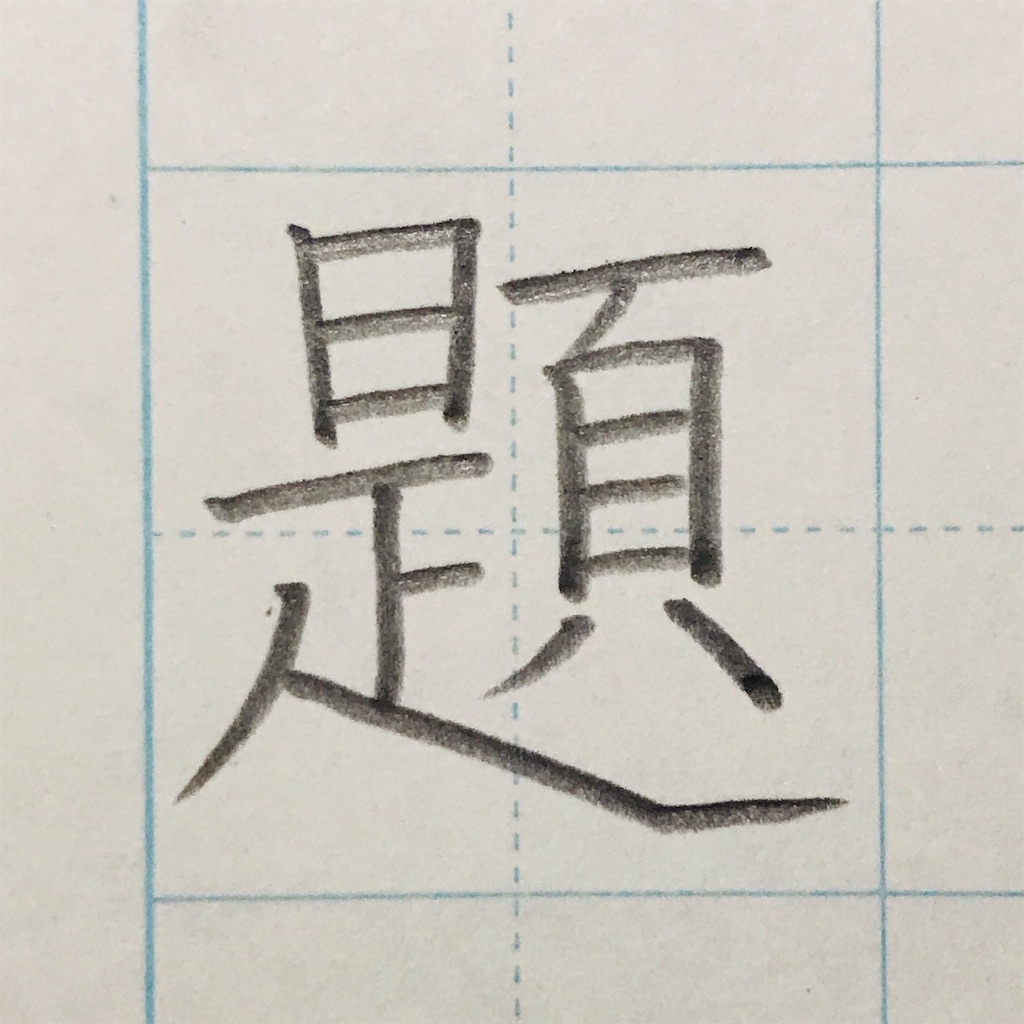
「題」の画数
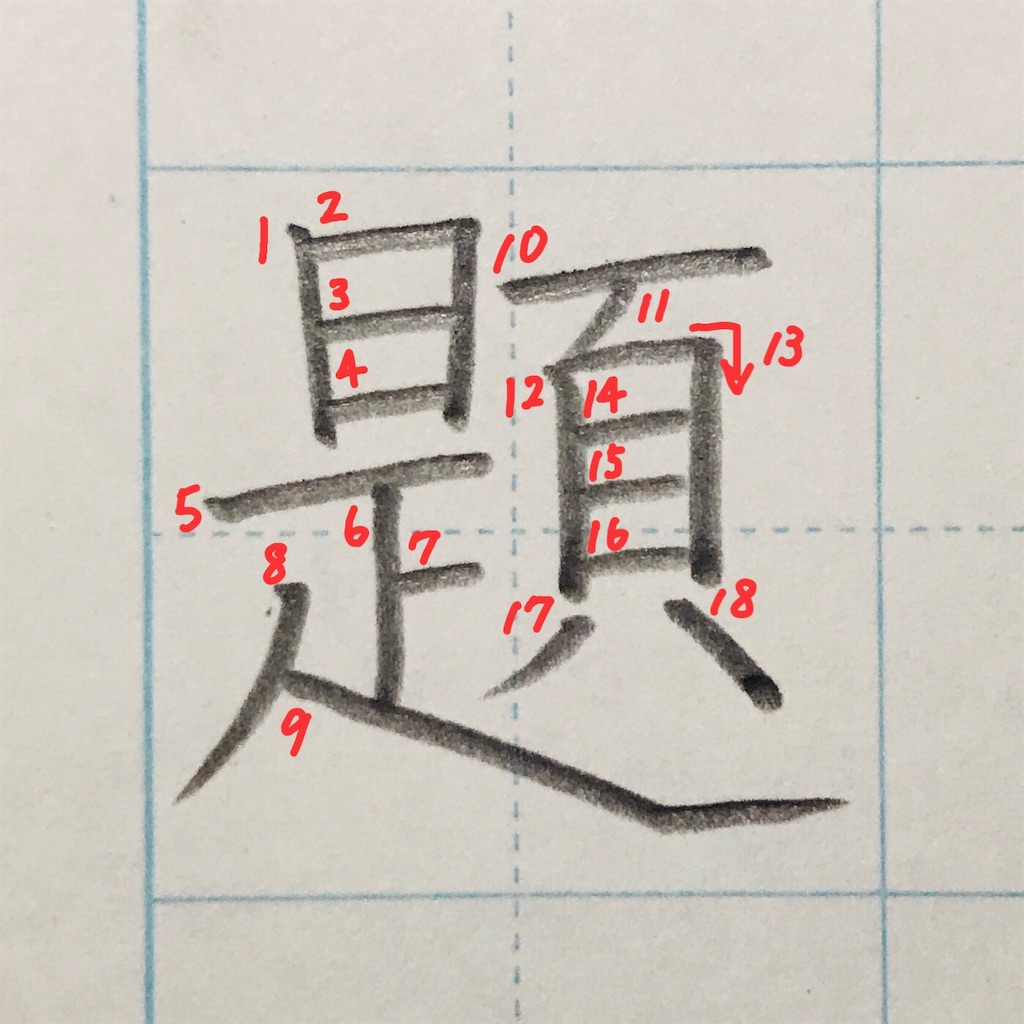
18画です。
「題」の構成
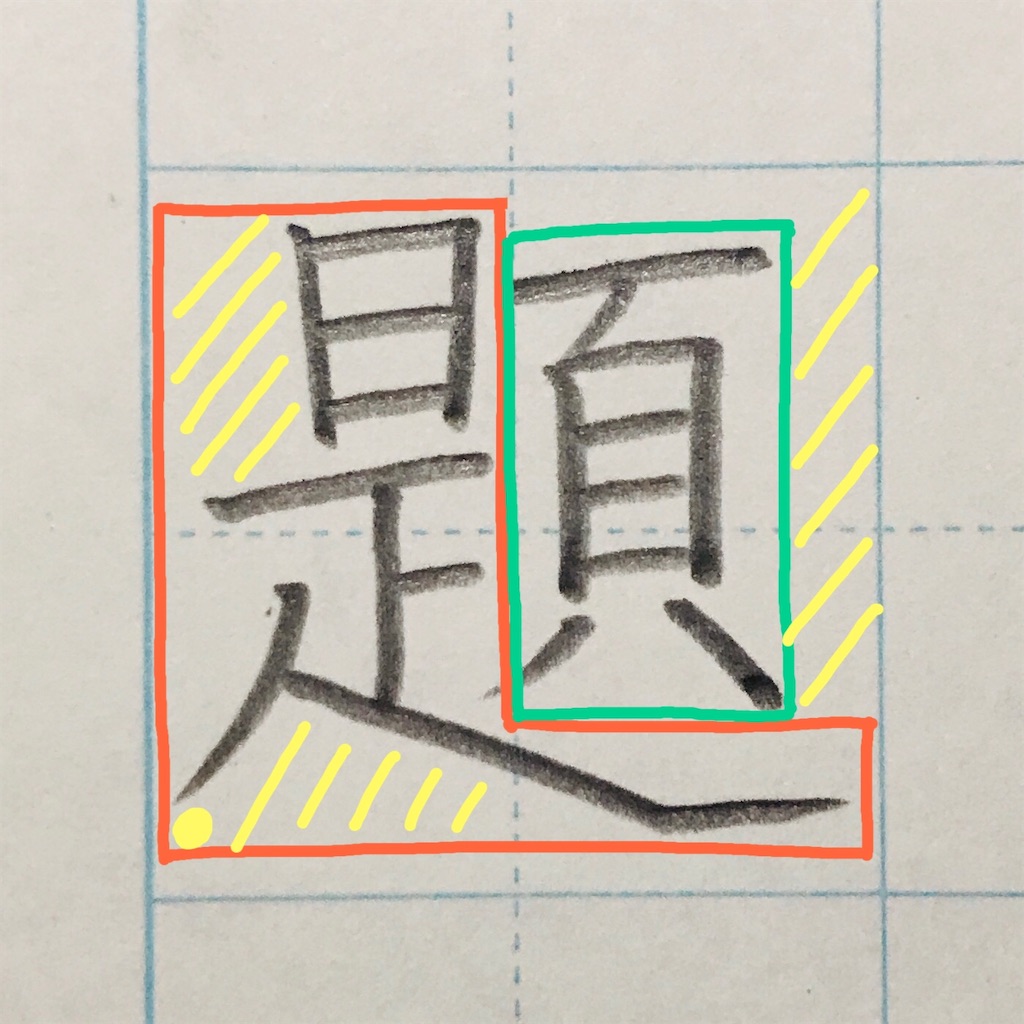
オレンジ色の部分におおがい(緑色)がしっかり乗るようにしましょう。
「題」のポイント
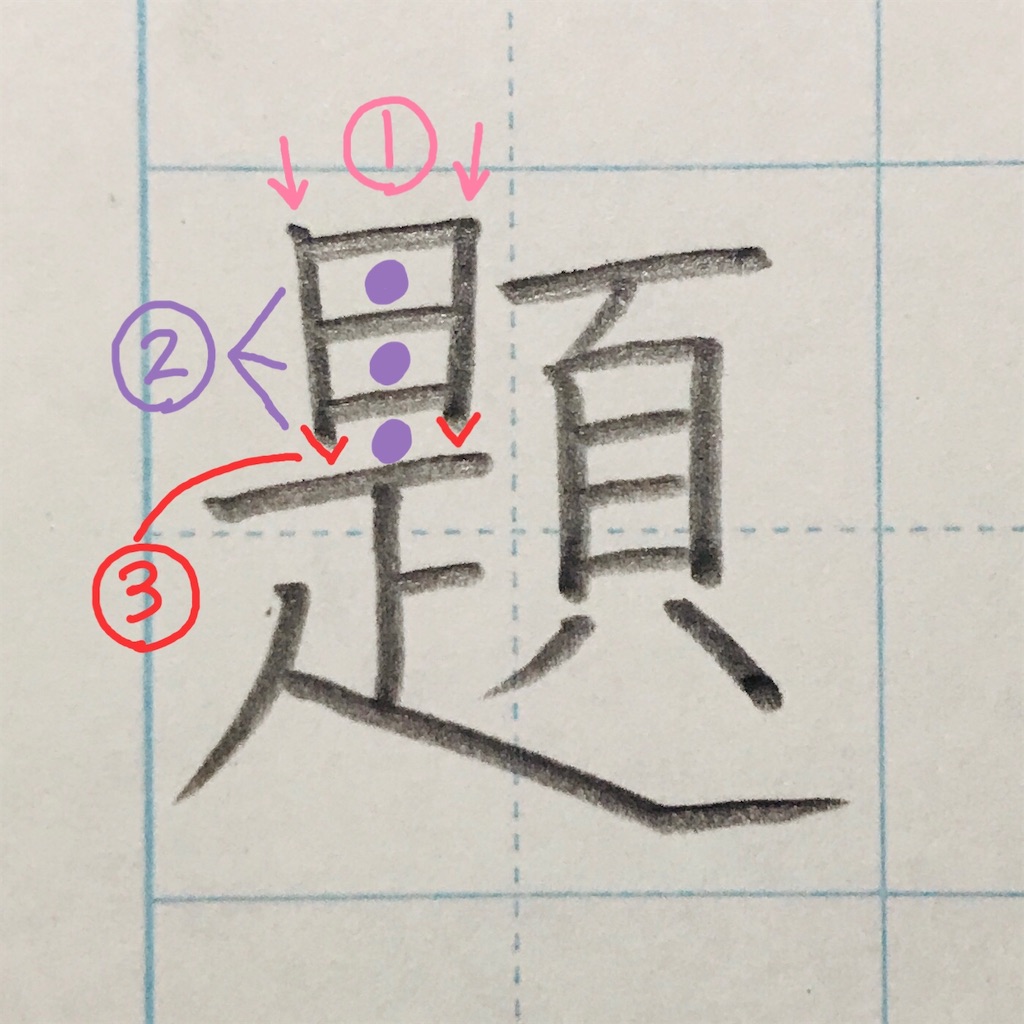
①同じ角度で少し内側に入れる。
②間隔を等しく。
③縦画を出す。
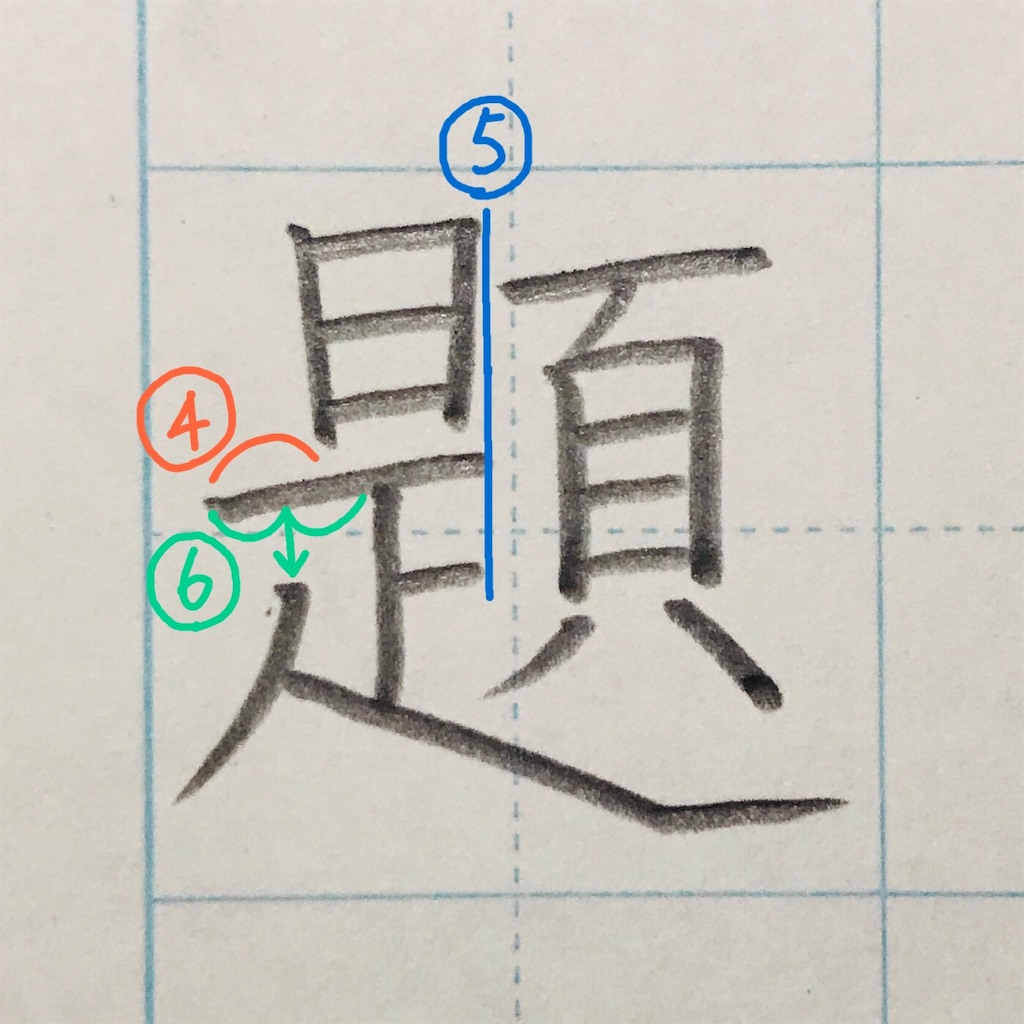
④左側を長く出す。
⑤右端は揃える。
⑥5画目左側のちょうど中心から8画目をスタートさせると◎。
⑦少し空ける。
⑧止めて、払う。
⑨「日」の中の横画と揃えて、少し長く。
⭐︎横画が多い字なので、きれいに右上がりに揃えるとスッキリ!
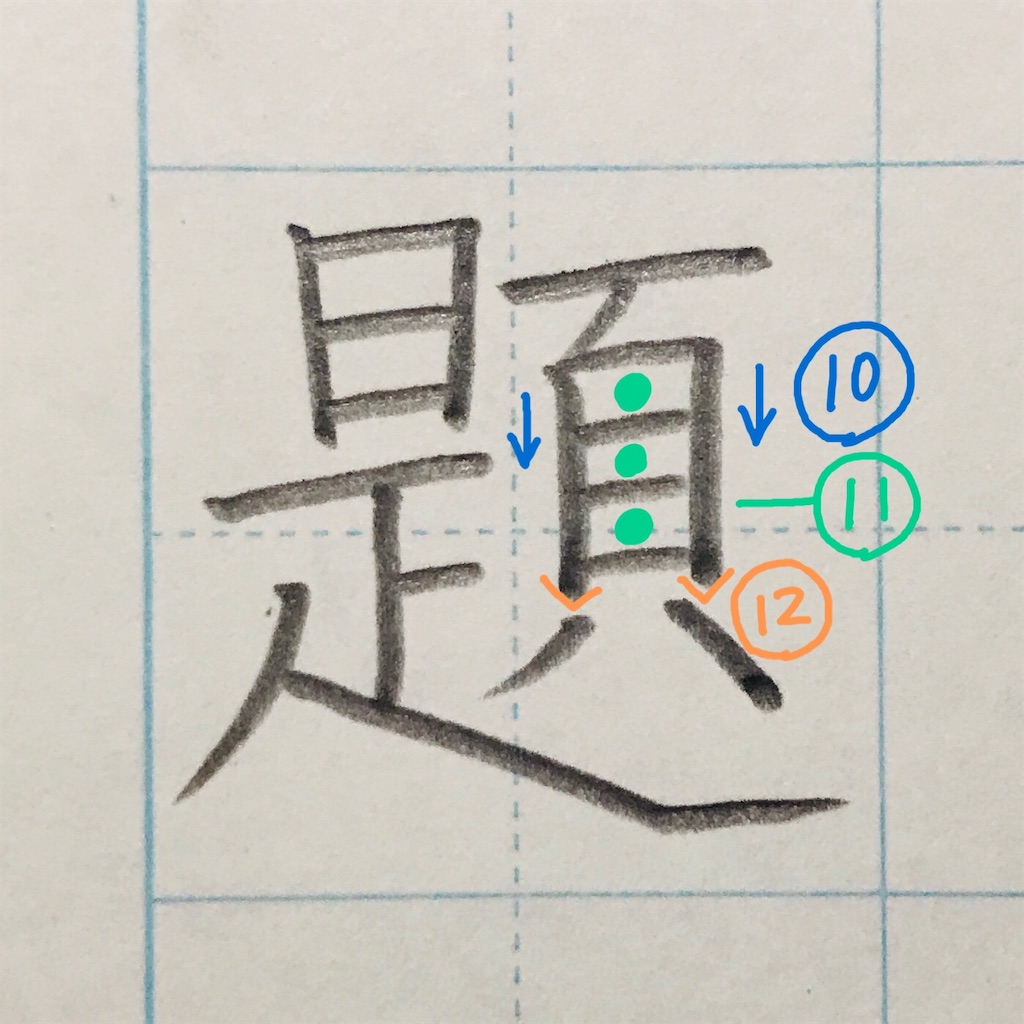
⑩まっすぐ。
⑪間隔を等しく。
⑫縦画を出す。
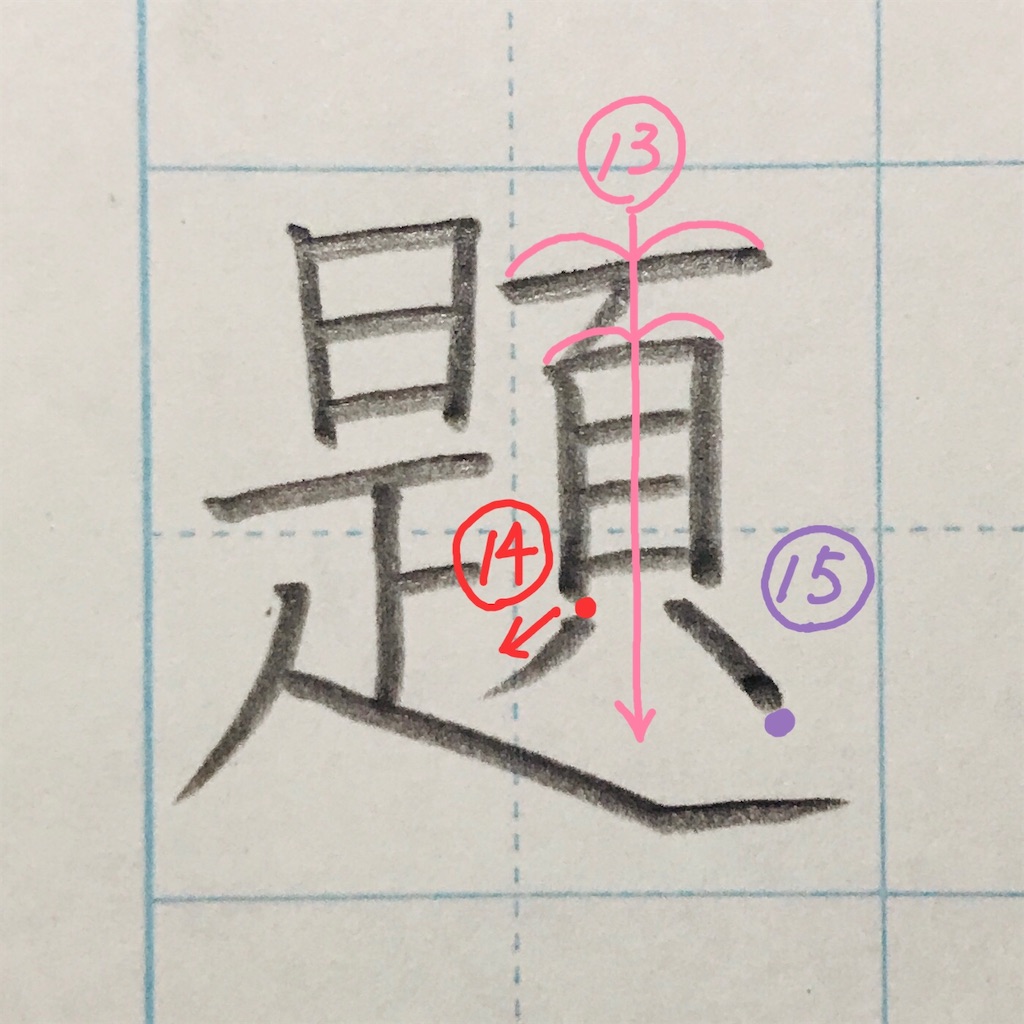
⑬それぞれの中心をしっかり通すと良いです。
⑭17画目は、12画目の縦画のすぐ下からスタート。
⑮最後は止める。
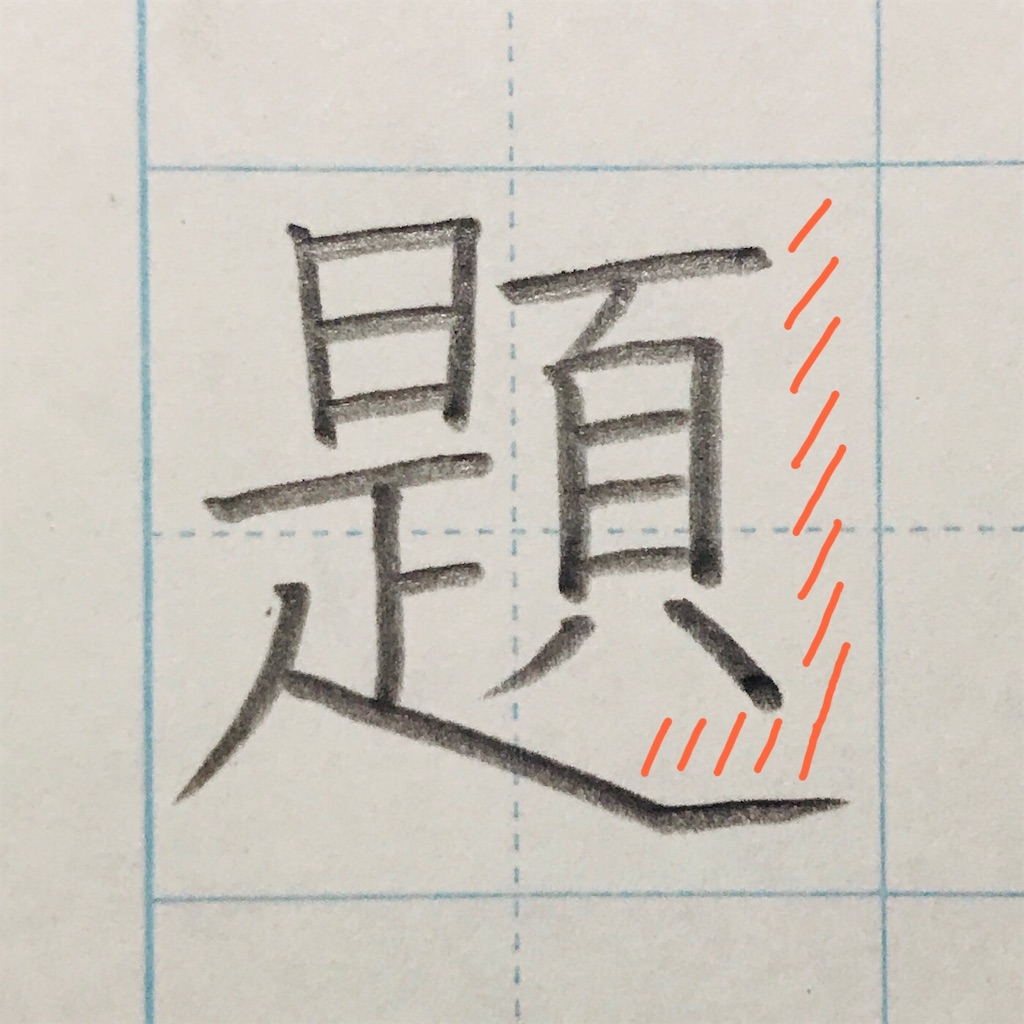
余白を作る。
完成!